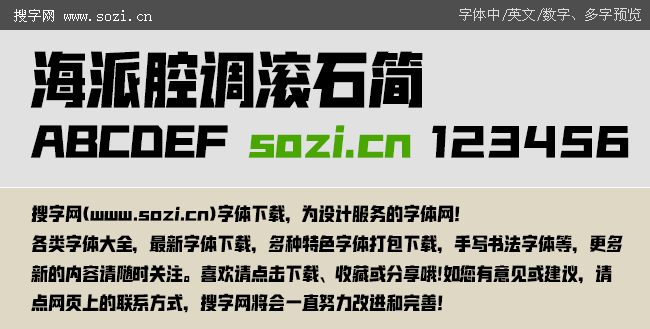
海派腔調(diào)滾石簡(jiǎn)
搜字網(wǎng)提供一款海派腔調(diào)滾石簡(jiǎn)中文字體下載,海派腔調(diào)滾石字體是一款粗壯醒目的中文字體,適合應(yīng)用于廣告設(shè)計(jì)、名片設(shè)計(jì)、包裝印刷、產(chǎn)品設(shè)計(jì)等應(yīng)用。